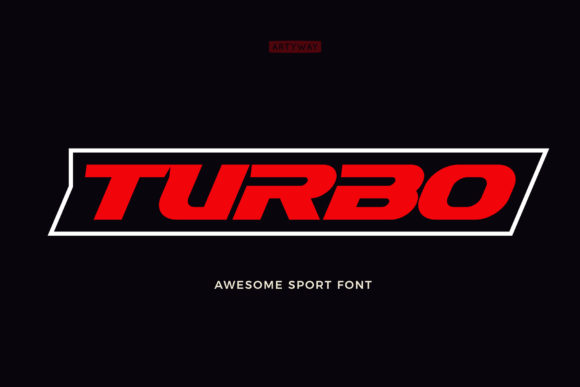
Turbo - это крутой и жирный шрифт. Он будет выглядеть потрясающе на любой плакатной листовке или принтере.
Используйте этот шрифт для создания дизайна и изучите его бесконечные возможности.